Це готичний шрифт, перекладення латинської абетки на кирилицю. Він підходить для написів, стилізованих під середньовіччя. (До речі, я кілька разів бачила у чоловіків татуювання, зроблені схожим шрифтом.) Готичний шрифт ідеально поєднується із середньовічними орнаментами. У композиції добре було б використовувати спрямованість готичного мистецтва вгору.
Можна написати цим декоративним шрифтом не весь текст, а тільки 1-ю велику літеру укрупненого розміру, яка називається буквица.
український алфавіт, написаний готичним шрифтом
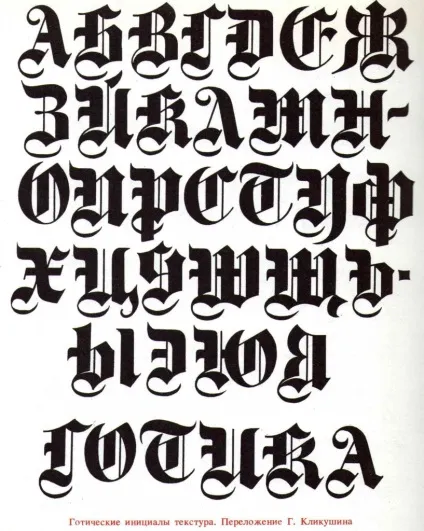
Джерело: книга «Декоративні шрифти: Для художньо-оформлювальних робіт», упорядник Г.Ф. Клікушін.
3 види середньовічного готичного письма
Любителям готики буде цікаво побачити приклади трьох видів готичного письма XII-XV століть:
а) круглоготіческое лист Ротунда, що використовувалося в Італії
б) фрактура (використовувалася у Франції)
в) текстура (буквально - ткання) - готичне лист Німеччини.